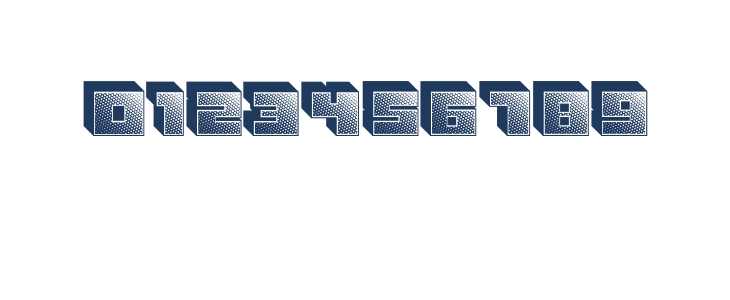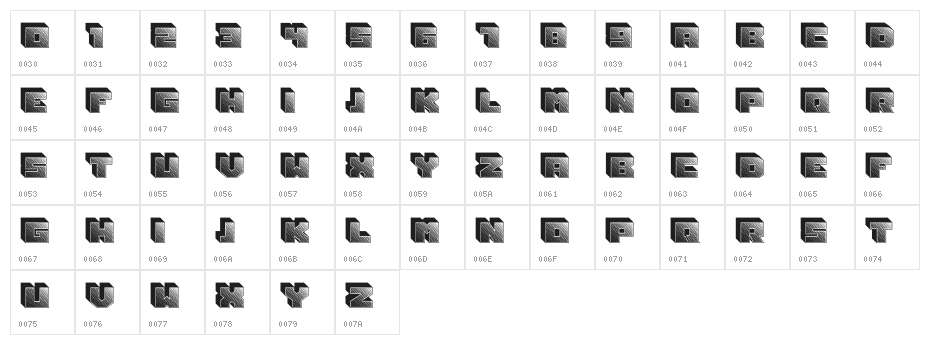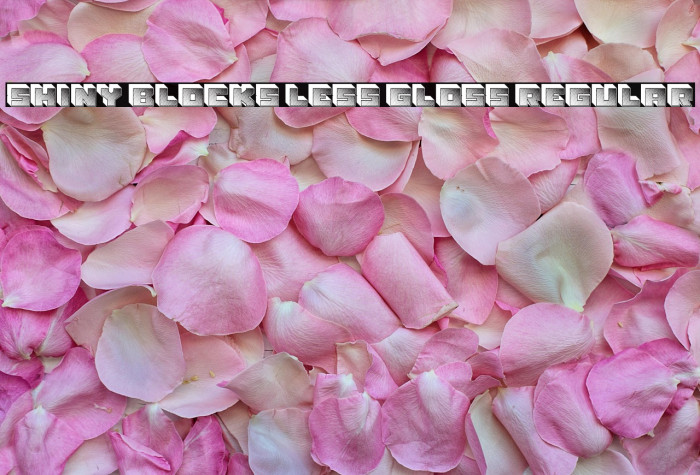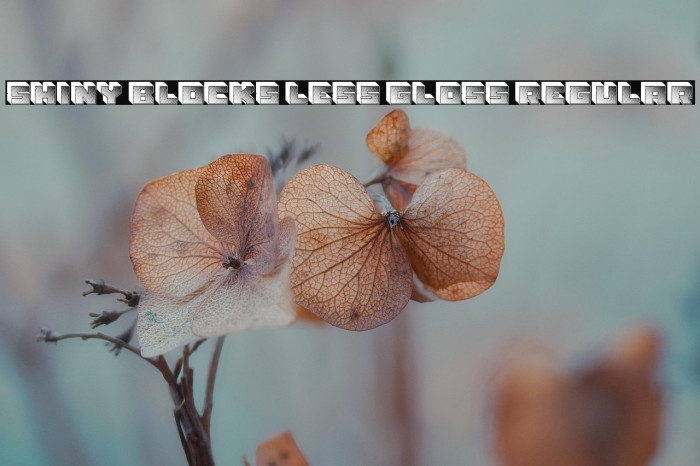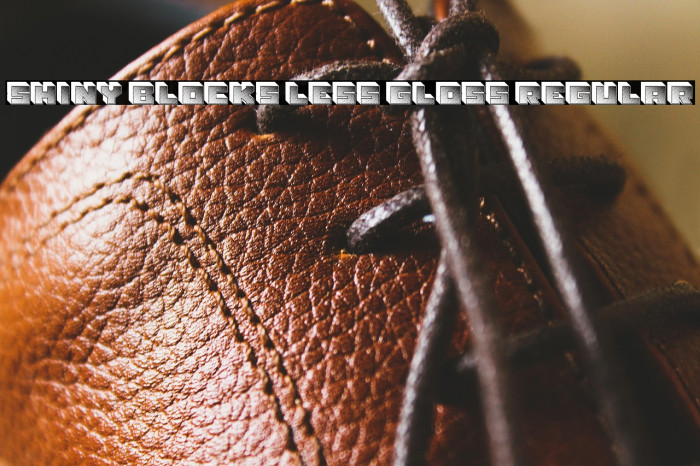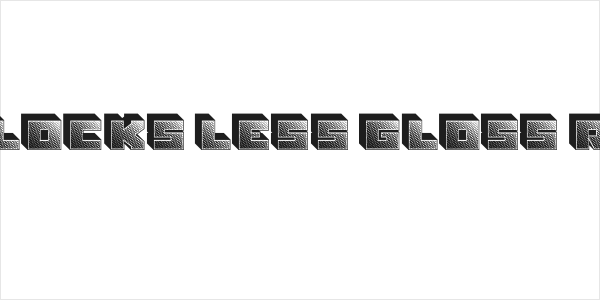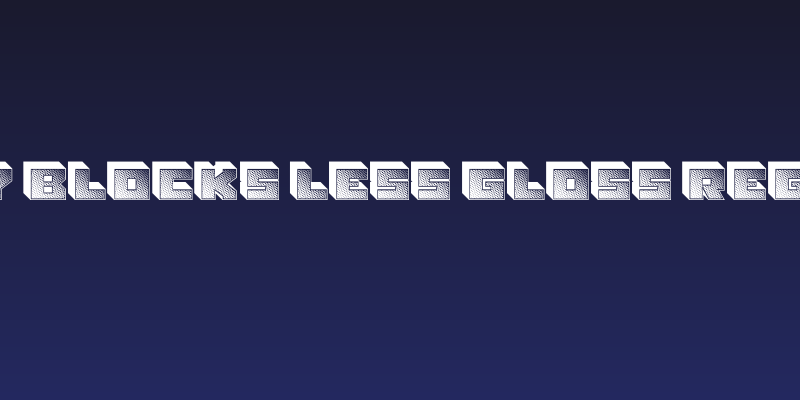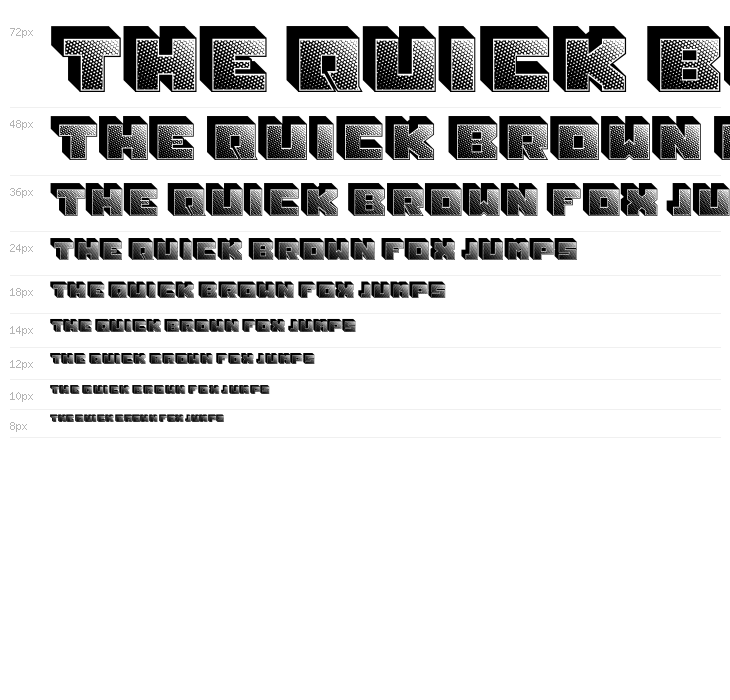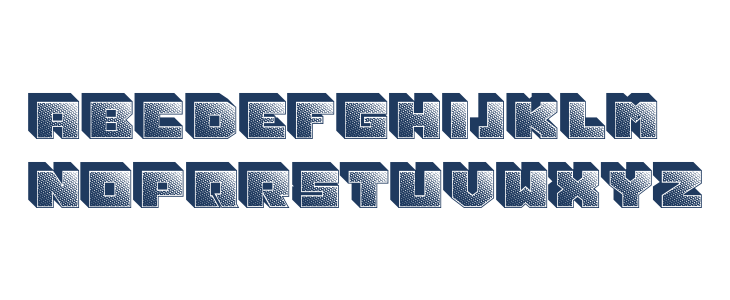
Shiny Blocks Less Gloss Regular Font
✎ 3D
| Proyectos propuestos | Ideal for posters, logos, video game graphics, and any project requiring a bold, eye-catching typeface. |